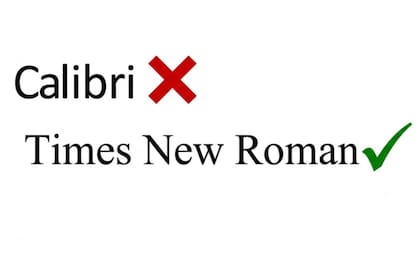
Inesperada batalla: Marco Rubio ordena restaurar la tipografía Times New Roman en los documentos del Departamento de Estado
La decisión del secretario de Estado desató un debate inesperado sobre criterios de diseño, accesibilidad y símbolos institucionales, en medio del desmantelamiento de políticas implementadas durante la gestión anterior
WASHINGTON.- El enfrentamiento cultural en Washington sumó esta semana un protagonista inesperado: la tipografía. El secretario de Estado Marco Rubio ordenó que todas las comunicaciones diplomáticas abandonen Calibri y regresen a Times New Roman, revirtiendo una política adoptada en 2023.
El movimiento quedó rápidamente inscripto en la batalla política que la nueva conducción del Departamento de Estado libra contra las iniciativas de diversidad, equidad e inclusión aplicadas durante el gobierno de Joe Biden.
Rubio calificó la adopción de Calibri como un cambio “equivocado”, producto de una visión que –según él– subordinó la tradición institucional a criterios supuestamente inclusivos.
La administración anterior había justificado la transición hacia Calibri en 2023 con argumentos de accesibilidad: la fuente sans serif beneficiaba a usuarios con baja visión, dislexia o lectores de pantalla.
Rubio rechazó esa lógica y sostuvo que el cambio no había mejorado la accesibilidad y que incluso implicó un gasto adicional que consideró injustificado.
The New York Times señaló que Calibri no es ajena a disputas políticas.
Diseñada para Microsoft a comienzos de los 2000 e instalada en millones de computadoras desde su adopción como fuente predeterminada en 2007, la tipografía se volvió parte de un escándalo internacional en 2017, cuando una investigación anticorrupción en Pakistán detectó que un documento presentado por Maryam Nawaz Sharif estaba fechado en 2006 pero había sido escrito en Calibri, que aún no era de uso público.
Ese detalle tipográfico, mínimo pero contundente, jugó un rol en la caída del entonces primer ministro Nawaz Sharif. El episodio cristalizó un debate recurrente entre serif y sans serif que ahora retoma vigencia en Washington.
El cambio tipográfico se inscribe dentro de un proceso más amplio en el que Rubio viene desmantelando oficinas y programas vinculados a políticas de diversidad en el Departamento de Estado.
En ese marco, la fuente se volvió un símbolo. La orden exige actualizar todos los documentos, plantillas y formularios oficiales, salvo dos excepciones estrictas: los textos relacionados con tratados internacionales y los nombramientos presidenciales, que deberán mantenerse en Courier New 12, una reliquia administrativa que sobrevivió a todos los cambios recientes.
El debate alrededor de las fuentes coincidió con un experimento interactivo del Washington Post que volvió a capturar la atención pública.
El medio creó un juego que invita a los usuarios a comparar diferentes tipografías y medir cuál les permite leer más rápido o con mayor comodidad.
La propuesta es sencilla: el lector enfrenta pruebas breves en las que debe identificar palabras, completar frases o distinguir caracteres bajo distintos estilos tipográficos.
El sistema calcula tiempos, precisión y preferencias subjetivas, ofreciendo un retrato personal de cómo cada fuente afecta la lectura.
La herramienta mostró que pequeñas variaciones –el grosor del trazo, el espaciado interno, la altura de las letras– pueden modificar notablemente la experiencia.
El experimento sirve para iluminar el costado técnico de una discusión que, en Washington, devino política.
Si Calibri ofrece mejor legibilidad para algunos usuarios y Times New Roman representa continuidad institucional, la tensión entre ambos enfoques quedó atrapada en una narrativa más amplia: la de un gobierno que busca reinstalar símbolos clásicos del Estado y desactivar sellos de la era Biden.
Rubio, en su orden, destacó el linaje “romano” de Times New Roman y describió la tipografía como portadora de formalidad y autoridad, dos valores que aspira a restituir en la comunicación diplomática.